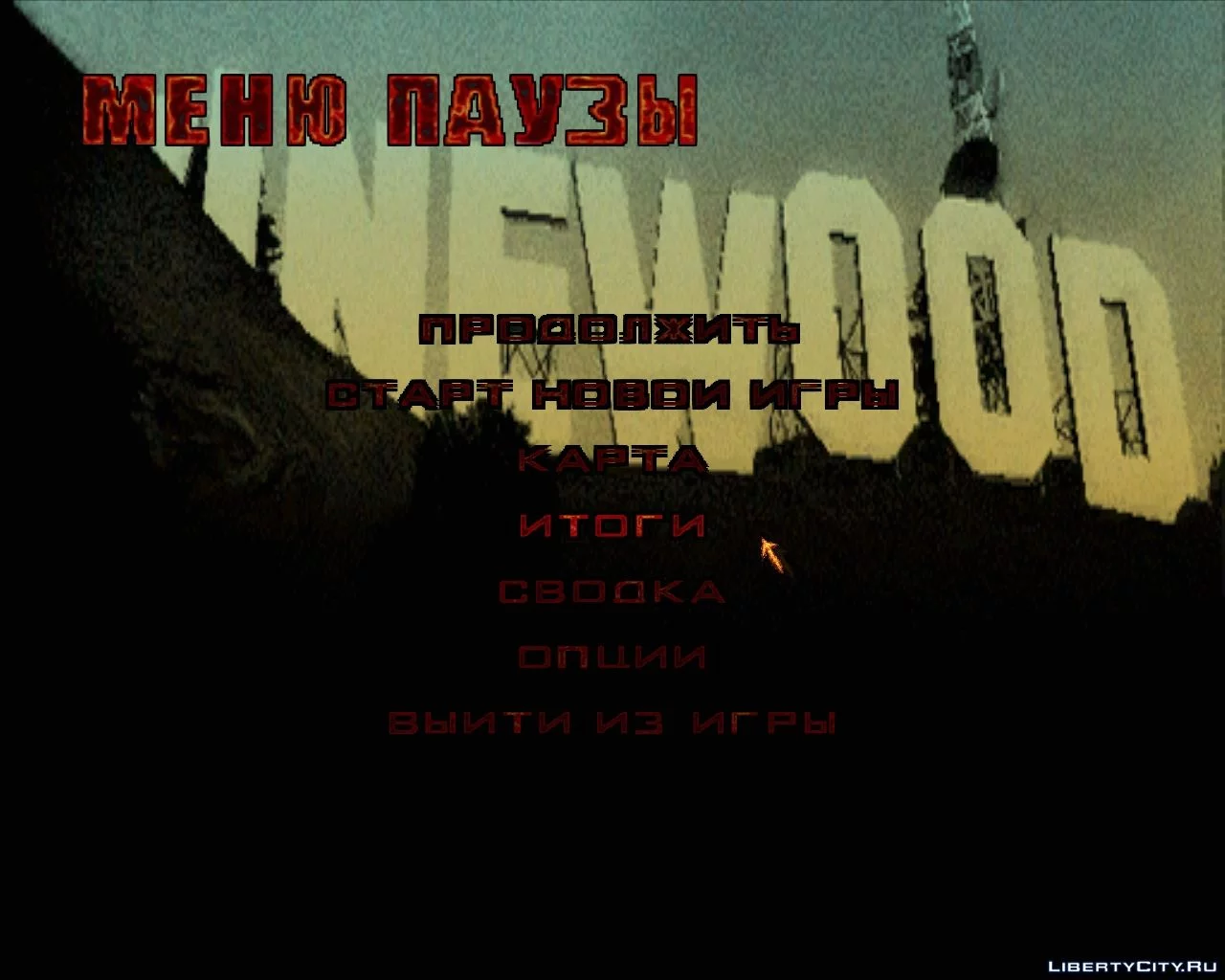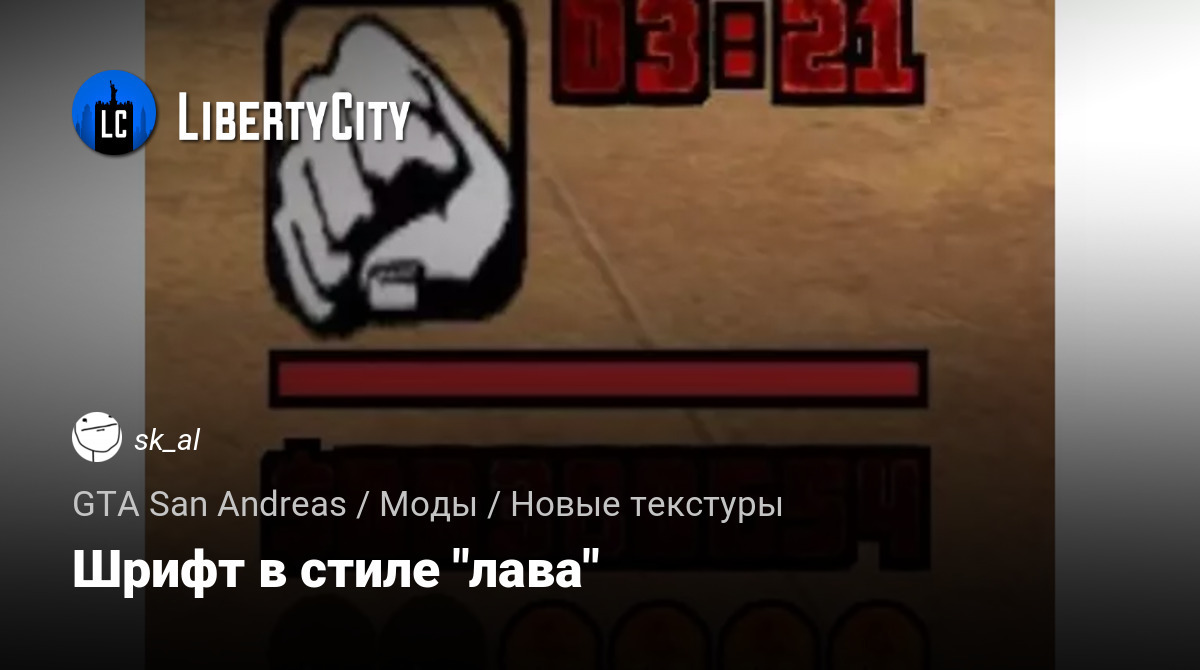
Шрифт в стиле "лава"
Моя первая работа над шрифтом.
Я заменил текстуры шрифта на текстуры в виде лавы, а также заменил указатель в меню на огненную стрелку.